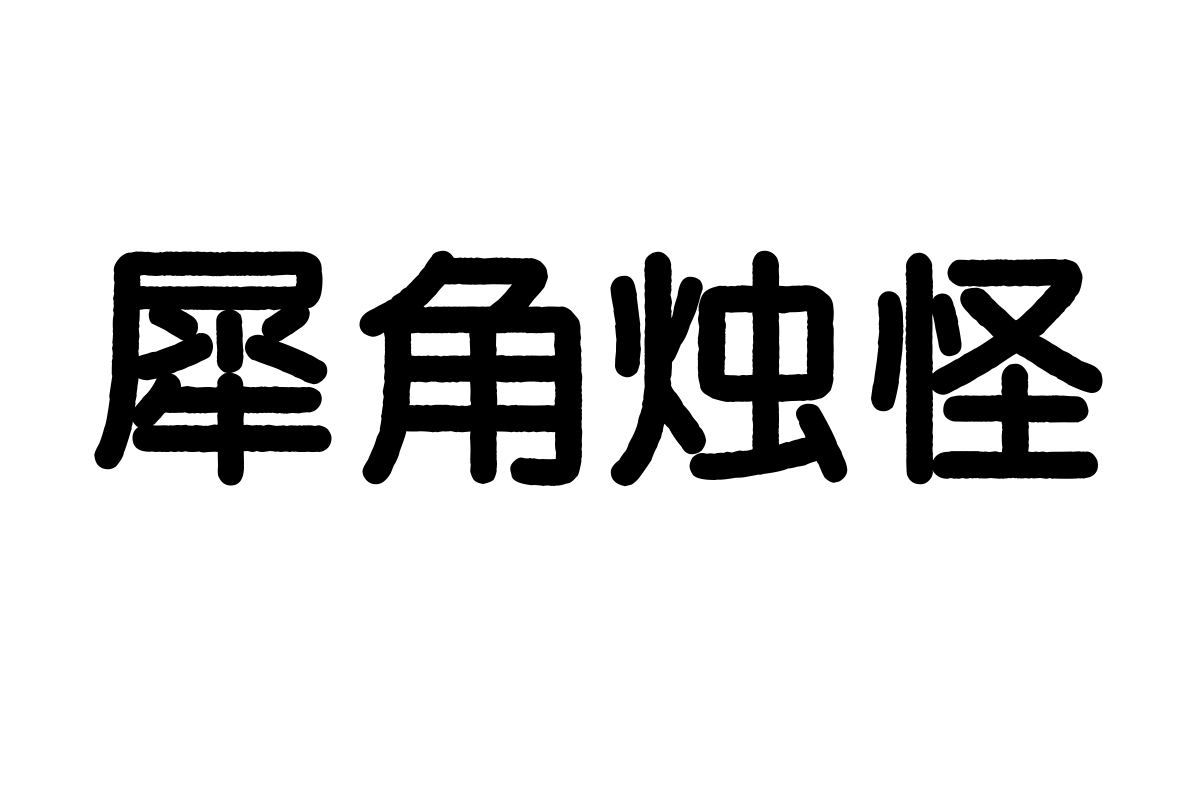
龚帆魅力粗圆字体是一种具有独特风格的中文字体,其特点是粗犷、圆润、有力。这种字体适合用于需要强调力量和活力的场合,如广告、海报、宣传册等。
龚帆魅力粗圆字体的特点如下:
1. 字形饱满:该字体的字形饱满,线条流畅,给人一种力量感。
2. 笔画粗细适中:该字体的笔画粗细适中,既不过于细弱,也不过于粗重,适合各种字体风格。
3. 结构紧凑:该字体的结构紧凑,字形紧凑,使得整体看起来更加协调。
4. 风格独特:龚帆魅力粗圆字体具有独特的风格,给人留下深刻印象。
5. 适用范围广泛:该字体适用于各种场合,如广告、海报、宣传册等,能够吸引人们的注意力。
总之,龚帆魅力粗圆字体是一种富有力量和活力的中文字体,适合用于需要强调力量和活力的场合。